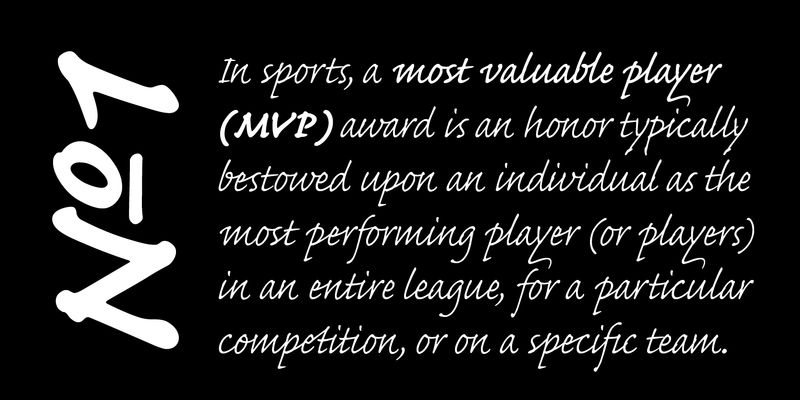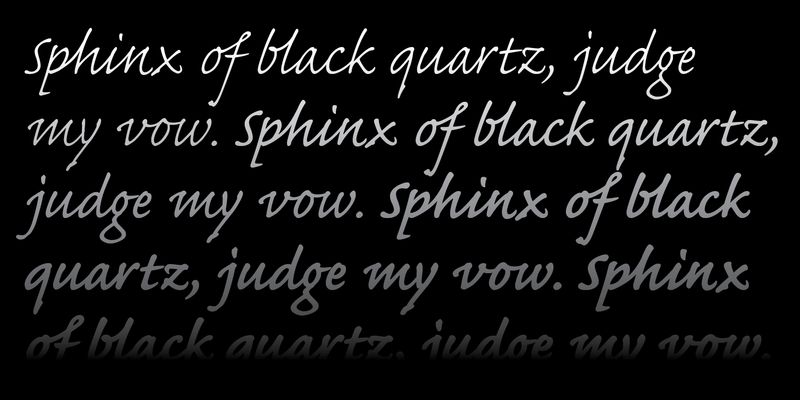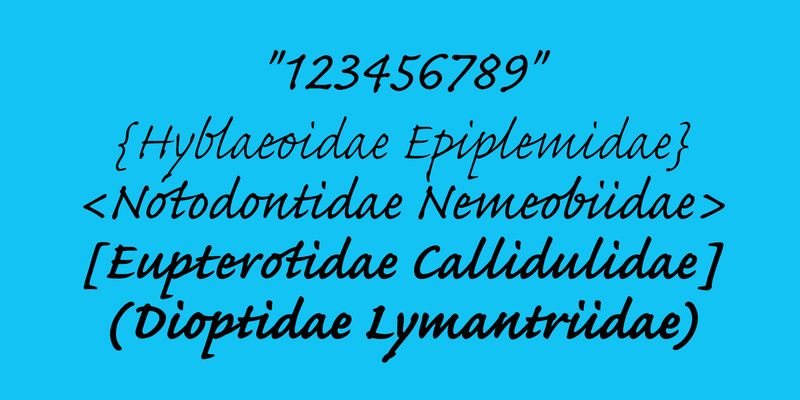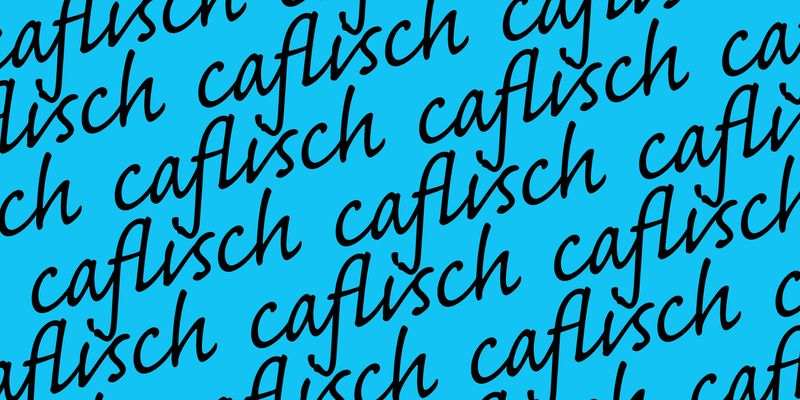
这种字体基于本世纪最杰出的平面设计师之一 Max Caflisch 的笔迹。Caflisch 在苏黎世担任平面艺术教师三十多年,著有数本关于排版的书籍,并设计了 1952 年的 Columna 字体。Caflisch 的笔迹流畅而又严谨,这是多年练习和热爱书法艺术的结果。设计师 Robert Slimbach 保留了 Caflisch 原笔迹的微妙之处和自然的字母连接,同时将其改编成排版合理且非常实用的脚本字体。Caflisch Script 于 1993 年首次发布,并于 2001 年在 OpenType 中进行了显著增强。Caflisch Script 可用于任何需要精细手写效果的地方,以及更复杂和实用的场合,例如书籍中的展示作品和广告排版。